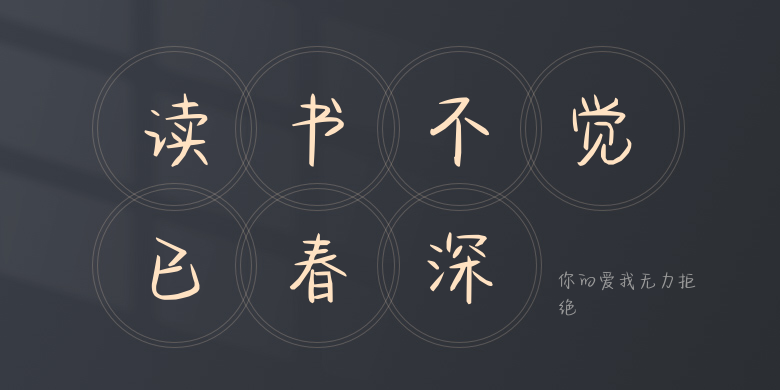
你的爱我无力拒绝
你的爱我无力拒绝,这款字体结构工整、笔画清晰,兼顾美观与易读性,适用于标题、正文、海报、包装、LOGO 等多种场景。字形优雅稳定,风格百搭耐看,适配日常排版与创意设计,让文字呈现更舒适、更具质感。你的爱我无力拒绝一笔一画,皆是细节,以均衡的比例、流畅的线条打造舒适视觉体验,字形端正大气,风格简约现代。无论是商业设计、品牌宣传还是日常排版,都能轻松驾驭,让文字更有格调与力量。你的爱我无力拒绝字体下载。